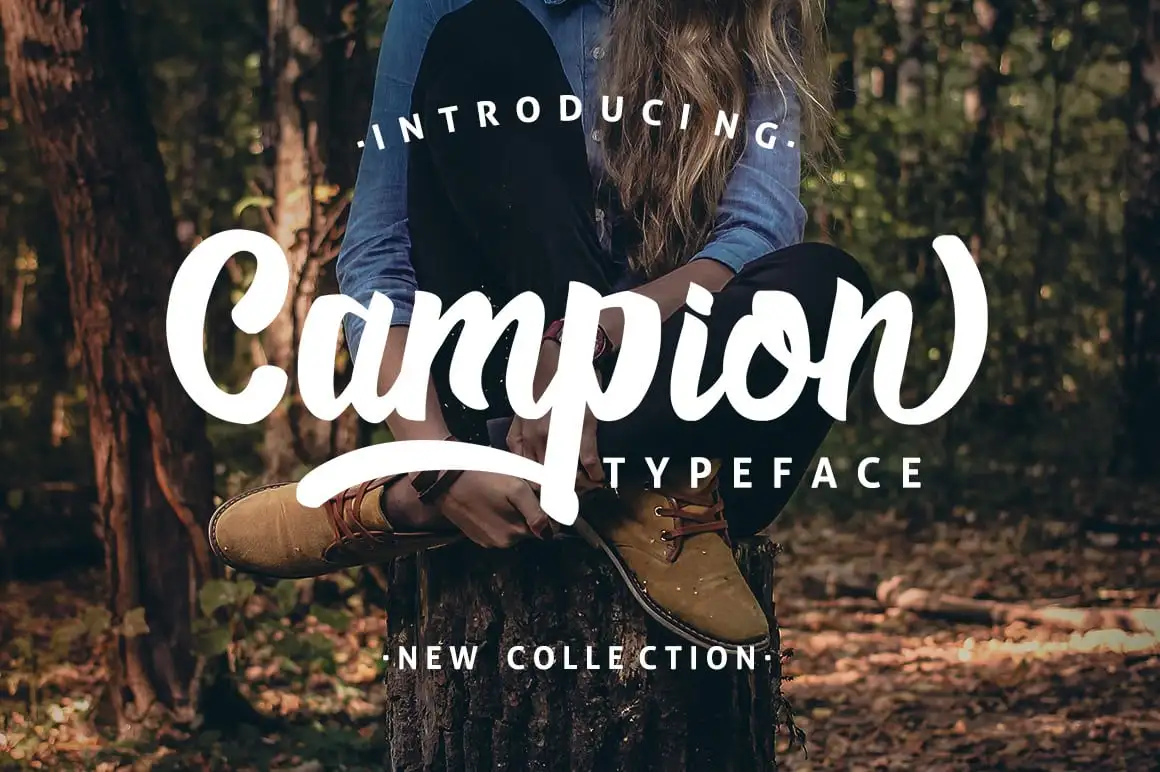
Campio Script Font – Download Grátis
A Fonte ‘Campio Script’ é uma elegante tipografia script que combina modernidade com a sofisticação dos estilos mais tradicionais. Perfeita para aplicar em diversas finalidades, essa fonte se destaca como ideal para cartões de casamento, embalando um toque romântico e especial à sua criação. Além disso, ela é excelente para criar design único e original em diversos materiais como logotipos, blogs, estoquistas, publicações, e muito mais. A fonte ‘Campio Script’ foi criada pelo designer 178-MC, idealizada para aqueles que buscam um estilo diferenciado sem abrir mão de uma aparência sofisticada. Ela é perfeita tanto para quem busca inovação quanto para designers profissionais buscando um toque distintivo em seus projetos.